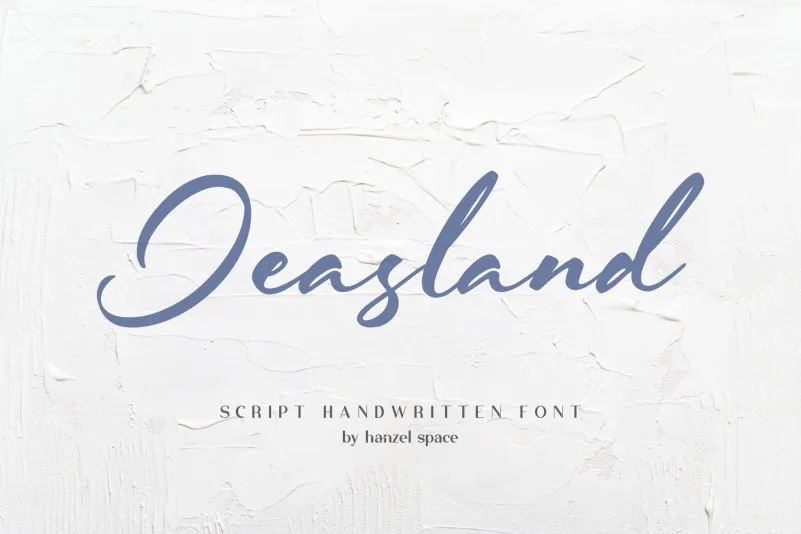
Jeasland Font – Download Grátis
A Jeasland Font é uma escolha perfeita para designers buscando incorporar estilos naturais e modernos em suas criações. Esse script tipo apresenta uma personalidade única, recomendado para quem deseja dar um toque acentuado aos seus projetos. Perfeito tanto para logos quanto para materiais de embalagem ou cartões de visita, essa fonte possui caracteres fluidos que permitem criar mensagens interessantes conforme sua preferência. Ideal para uma variedade de aplicativos como logotipos, posters, etiquetas em camisas, cartas de cumprimento, cards empresariais e convites de casamento, a Jeasland Font permite incorporar um toque autêntico e moderno à sua criação.